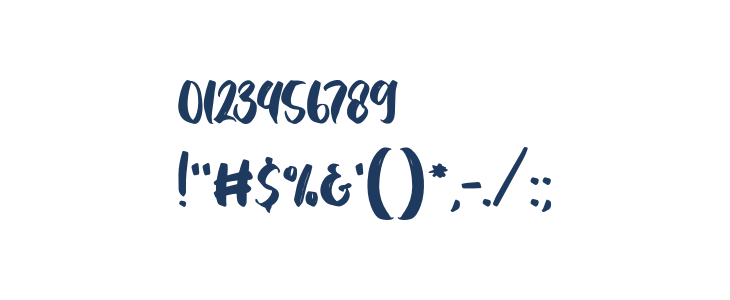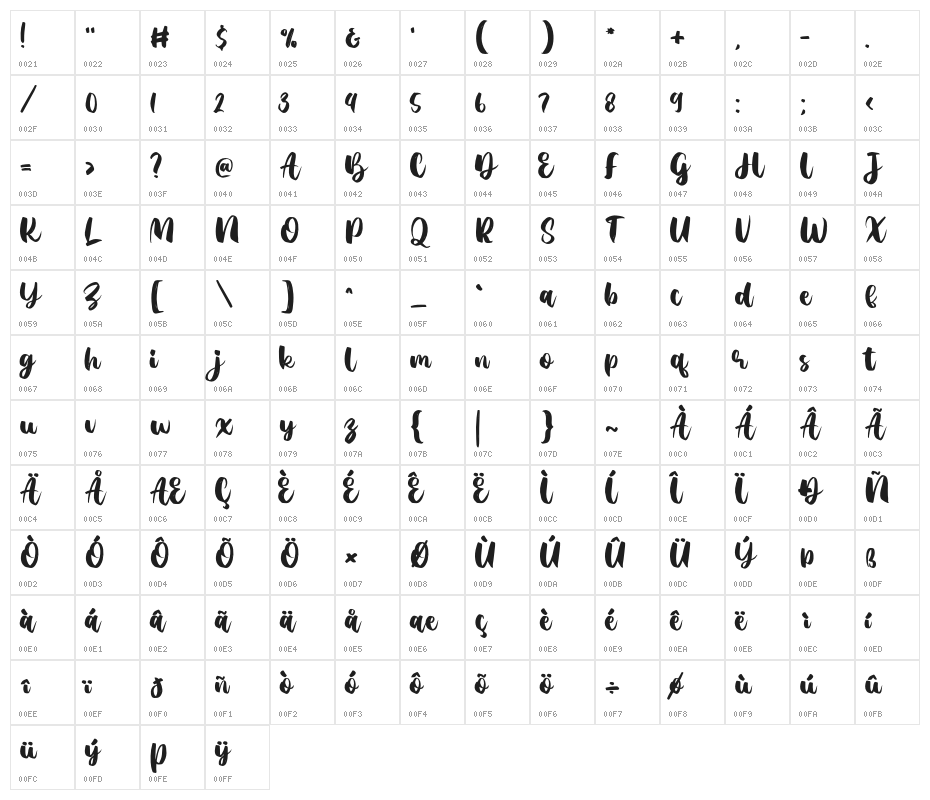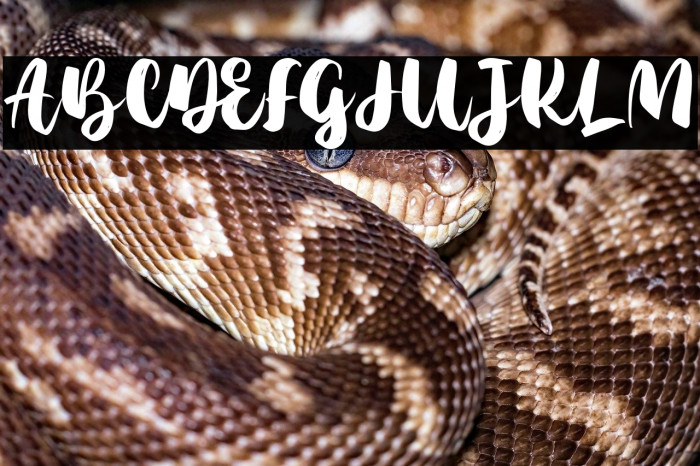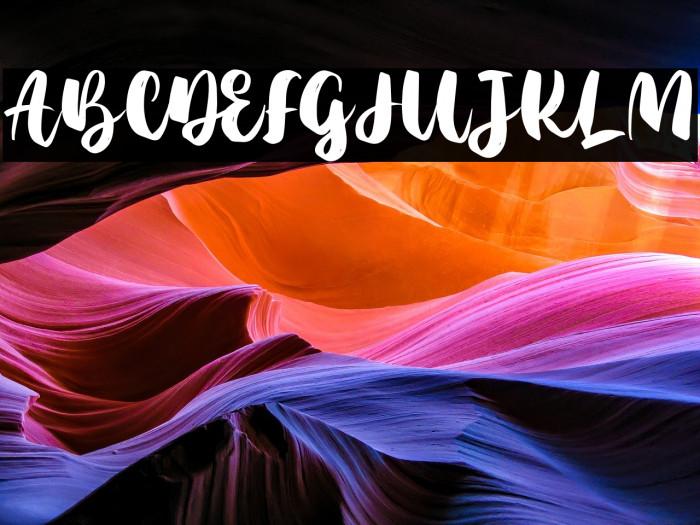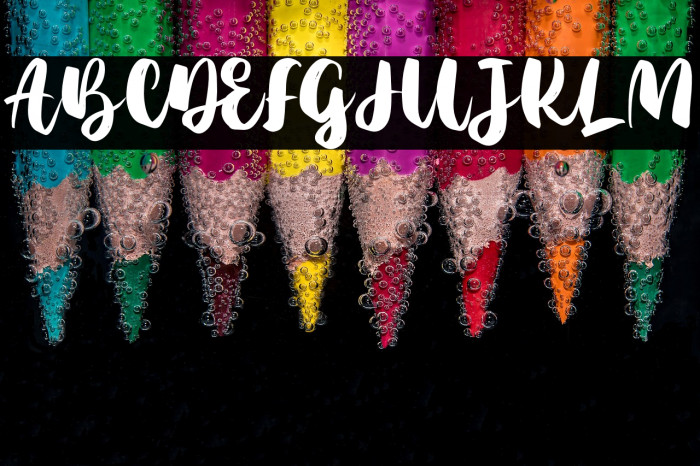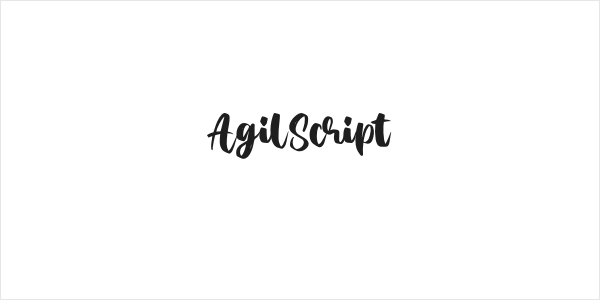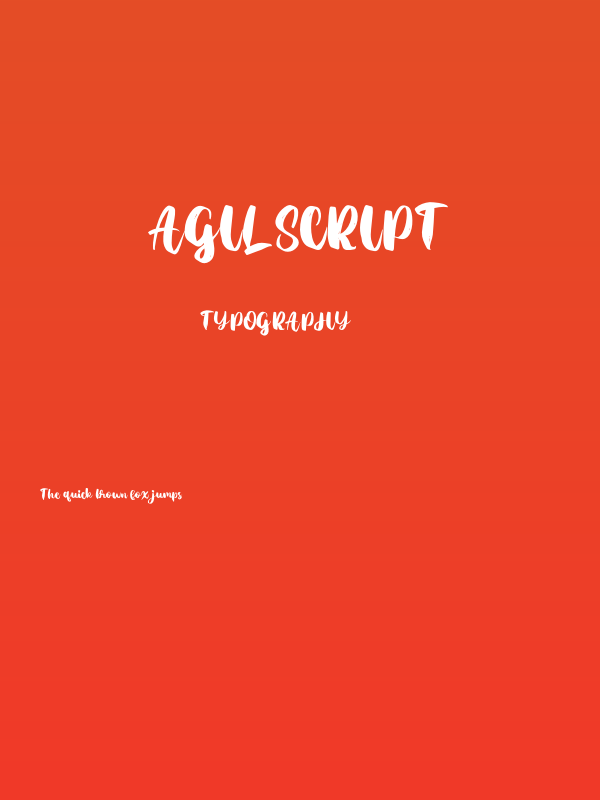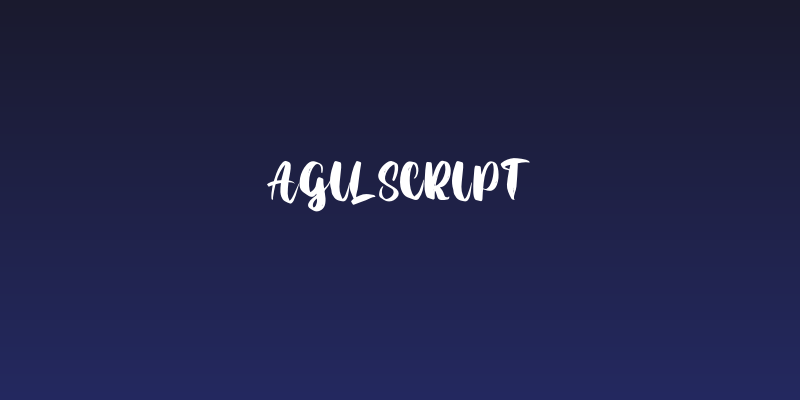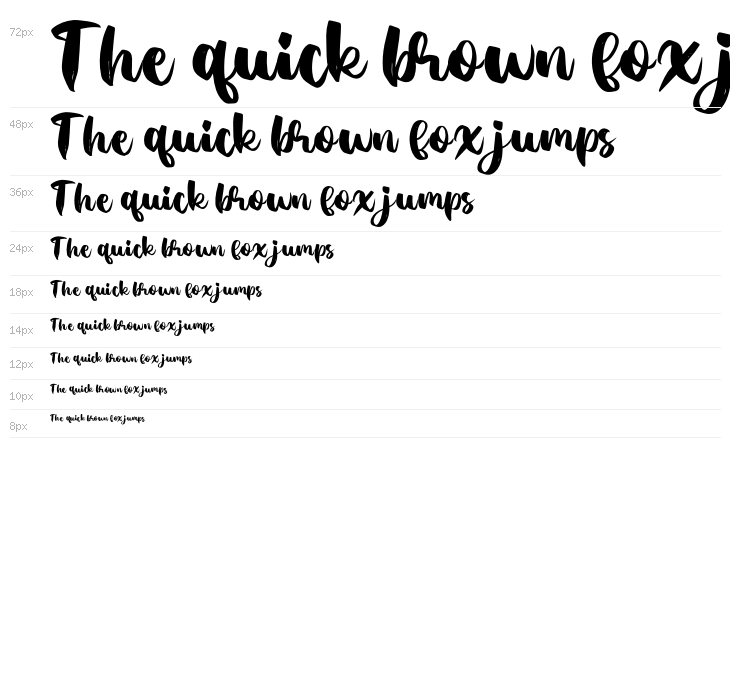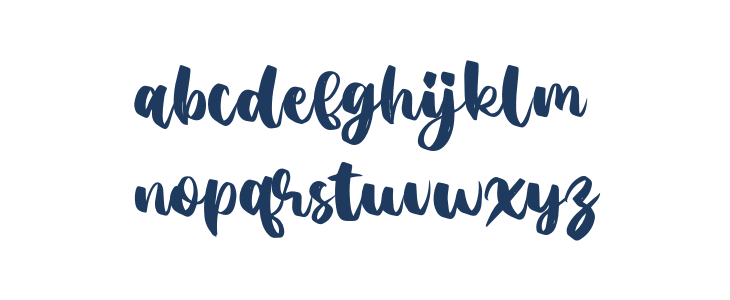
AgilScript Font
| Область применения | Logos, Headlines, Decorative text |
| Рекомендуемые проекты | Ideal for invitations, greeting cards, branding materials, and any project needing a personal touch. |
AgilScript